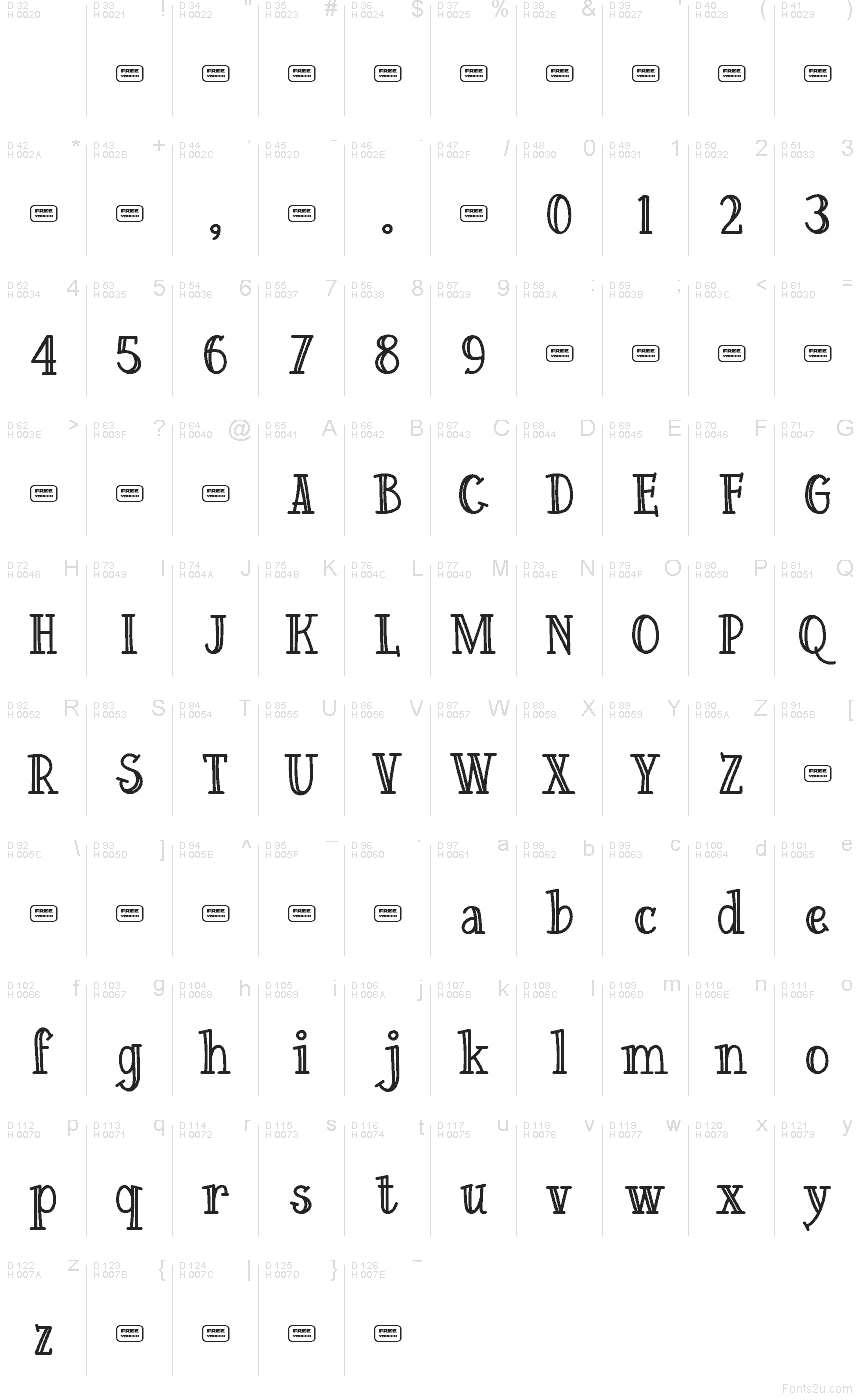
Storiffy od Typefactory je bezplatné písmo typu display, které formují prohnuté křivky, ohnuté dříky a lehce neotřelý rytmus, díky němuž jsou písmena neustále v pohybu. Design kombinuje vysoké úzké tvary se širokými oblými tahy, což mu dodává vzhled jako z pohádkové knížky, spíše než jen běžný dekorativní styl.
Díky tomuto nerovnoměrnému, ručně kreslenému rázu je Storiffy přirozenou volbou pro knižní obálky, branding kaváren, obaly, titulky plakátů a grafiku na sociální sítě, která potřebuje přátelštější tvář. Hodí se také pro pozvánky na dětské akce nebo vývěsní štíty butiků, kde zaoblené detaily a mírně nakloněná struktura dodávají krátkým slovům nezaměnitelný charakter.
Storiffy je písmo typu display.